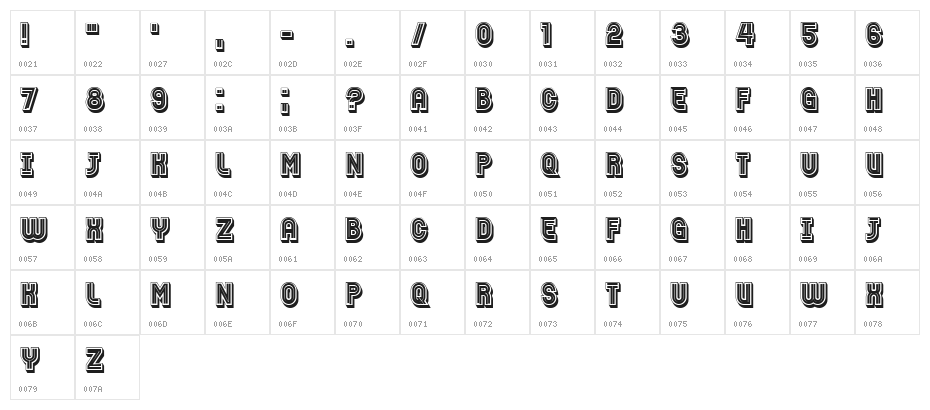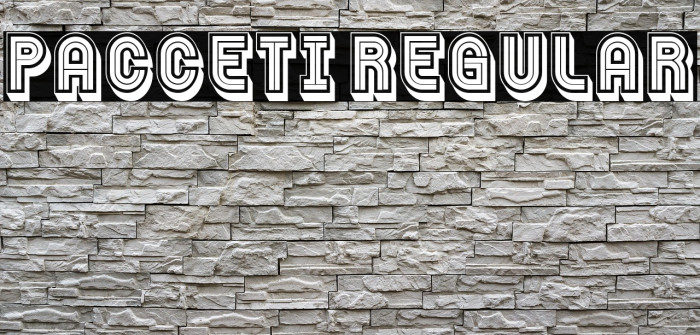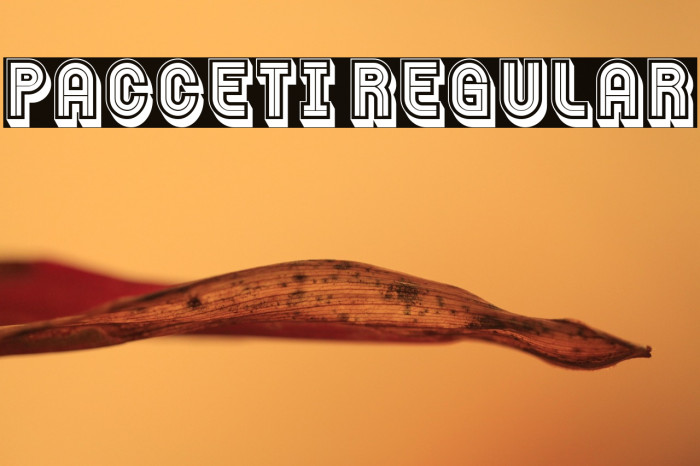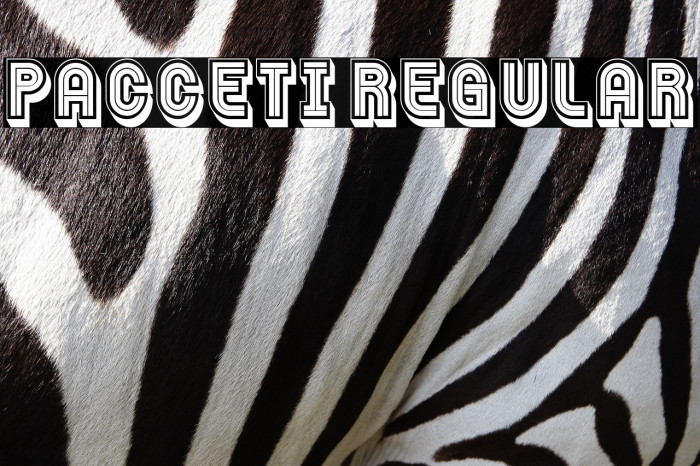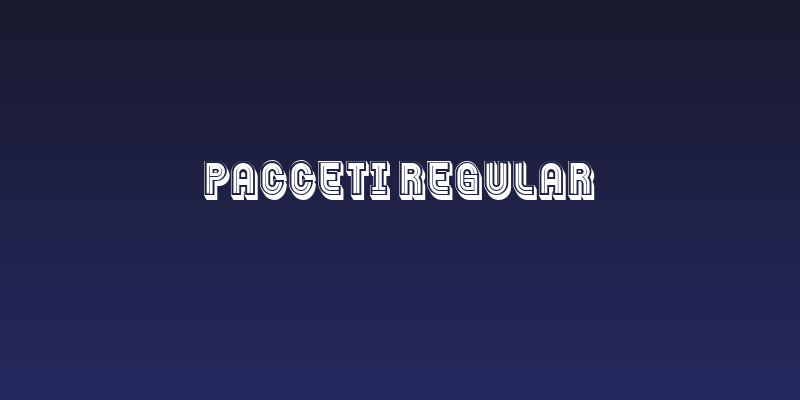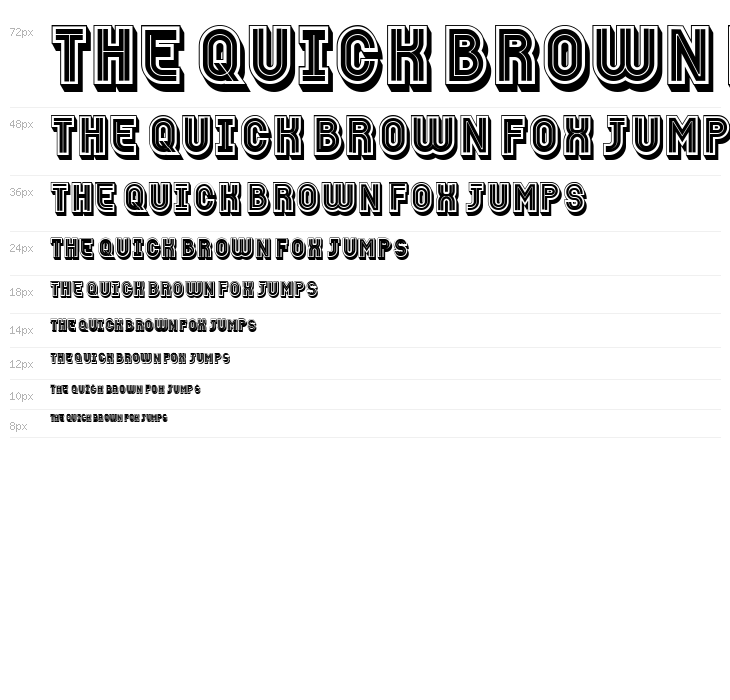
Pacceti Regular Font
| Proyectos propuestos | Ideal for posters, headlines, logos, and branding materials that require a bold and eye-catching design. |